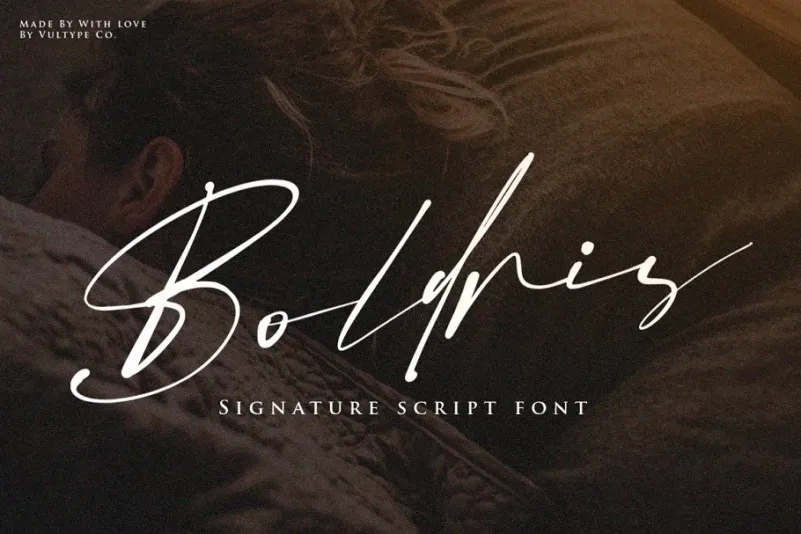
A Boldris Font é uma elegante seleção de letra escrita à mão que se destaca tanto no cotidiano quanto na contemporaneidade. Esta tipografia tem traços de canetinha com contraste, incluindo um toque leve e divertido nas letras. Ela combina elementos do estilo da escrita à mão moderna, oferecendo ligaturas e estilos alternativos para adicionar um ar único e vibrante às suas criações gráficas. A Boldris é perfeita para designers que buscam uma fonte de escrita à mão contemporânea e versátil, capaz de dar um toque especial a qualquer projeto. Seja você criando cartazes para campanhas de marketing ou preparando documentos pessoais, esta fonte será sua companheira ideal em suas tarefas diarias no design.